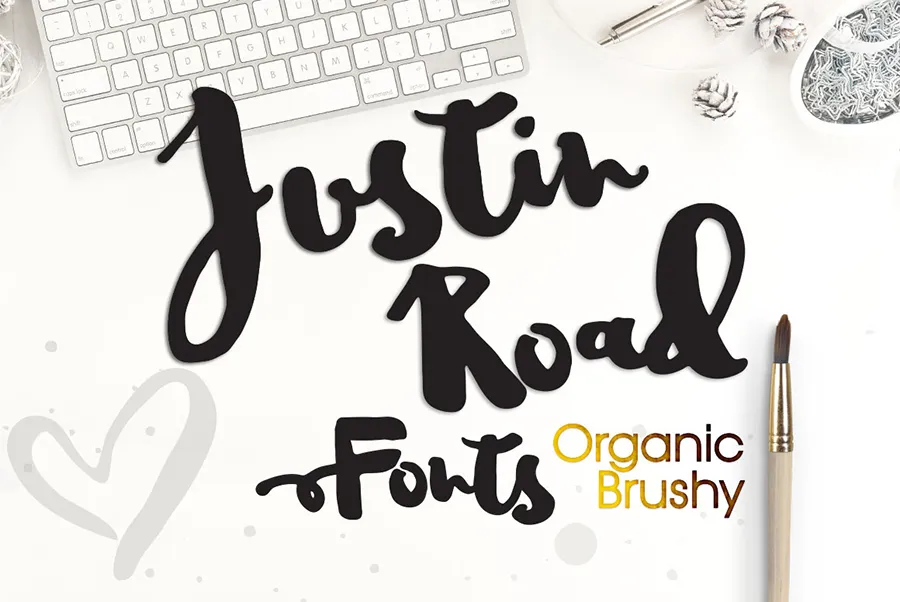
Justin Road Font – Download Grátis
A Justin Road é uma fonte livre com um estilo natural e desenhado por pincel. Essa linda fonte alegre está pronta para destacar seus designs entre as multidões. Esta bela fonte de borracha é disponível no formato OpenType, o que permite sua utilização tanto em projetos pessoais quanto comerciais. Com seu charme e estilo vibrante, ela certamente dará um toque especial aos seus trabalhos gráficos. Uma excelente opção para designers buscando algo único e criativo. A fonte é perfeita para criar uma impressão profissional que se destaca no mercado, seja para uso pessoal ou comercial. Não hesite em experimentar a Justin Road para adicionar um toque especial à sua próxima criação visual.